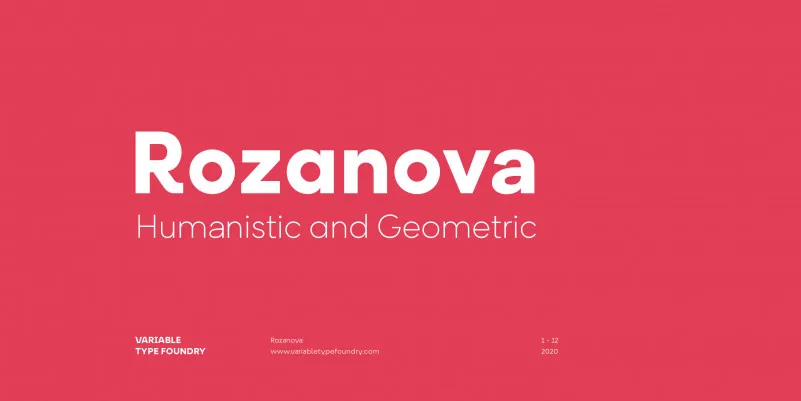
A Rozanova Font Family é uma tipografia sem serif que apresenta proporções e formas únicas e distintas, tornando-a funcional, legível e com personalidade. Suas formas possuem um caráter único, fazendo dela uma fonte versátil e dinâmica, facilmente reconhecível e apropriada para projetos editoriais, uso corporativo e identidades de marca robustas, como posters, logotipos e embalagens. Com sua riqueza gráfica e seu design único, essa fonte sem serif proporciona uma maneira moderna e criativa de ilustrar qualquer projeto visual, permitindo que o designer a personalize para criar um estilo único e forte.
Designer: Variable Type Foundry